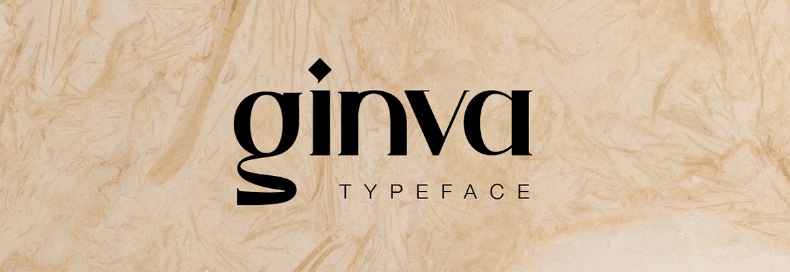
A Ginva Font é uma elegante escolha para designers buscando um tipo com forma fluida e proporções perfeitas. Desenvolvida pelo arquiteto Wassim Awadallah, esta fonte serifada oferece um toque artístico que se destaca em qualquer projeto visual. Com seu design limpo e proporção cuidadosamente calculada, a Ginva é ideal para aplicativos que valorizam tanto letras minúsculas quanto maiúsculas. A característica mais interessante da Ginva Font é sua linguagem all lowercase, um padrão raro em fontes serifadas. O designer pretendeu incorporar uma versão com letras maiúsculas e caracteres especiais para expandir ainda mais o seu uso. Este tipo de design atento à proporção faz dela uma escolha ótima para qualquer projeto que valoriza a estética moderna e sofisticada, sem deixar de lado a elegância do estilo serifado. Em suma, a Ginva Font é um excelente recurso para designers que desejam trazer um toque único e artístico às suas criações digitais. Com sua proposta de design cuidadosamente considerada, ela é perfeita tanto para aplicações digitais quanto impressas.